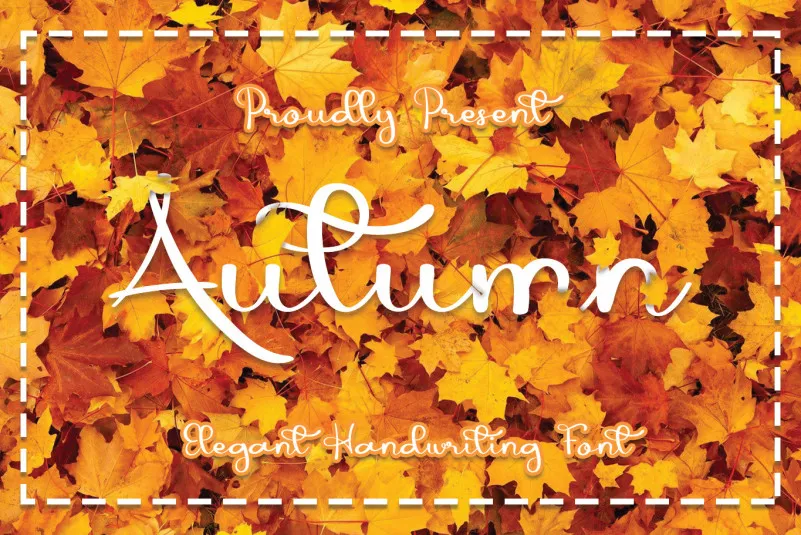
Autumn Font – Fonte Grátis
Autumn Font
Aqui está uma descrição em português do Brasil para a página de download da fonte ‘Autumn Font’, seguindo as instruções fornecidas: Esta fonte, chamada Autumn, é um belo exemplar de script moderno, cuidadosamente elaborado e detalhado. Ela traz uma atmosfera única que irá complementar qualquer projeto gráfico em sua biblioteca de fonts. Independente da temática do seu trabalho, esta font é perfeitamente adaptável, tornando-se um excelente recurso para dar vida aos seus projetos digitais. Seja em um design gráfico, criação de websites ou aplicativos móveis, Autumn é uma escolha inteligente que certamente enriquecerá qualquer obra sua. Composta com precisão e ricos detalhes, esta font não apenas oferece beleza visual, mas também se ajusta perfeitamente aos mais variados estilos e necessidades do design. Como um designer gráfico atento a cada detalhe, Autumn é uma escolha inteligente para complementar seu portfólio de fonts.